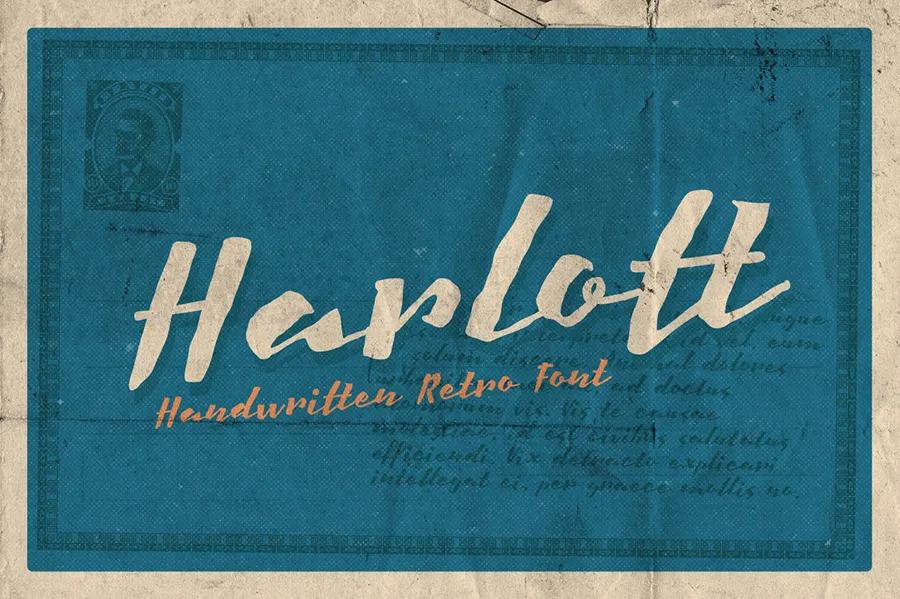
Harlott Font – Download Grátis
Harlott Font é uma tipografia brush que inspira-se na letra à mão tradicional com esferográfica. Inspirada pelos traços naturais do estilo calligrafia à mão, essa fonte livre oferece um efeito de letra a mão que se assemelha ao desenho direto de uma esferográfica. Perfeita para criações de logomarca ou parte da identidade visual, capas de jornal, headlines, ou qualquer tipo de aplicação visível, Harlott é ideal tanto para t-shirts quanto para outras aplicações gráficas, adicionando um toque autêntico e elegante a sua obra.